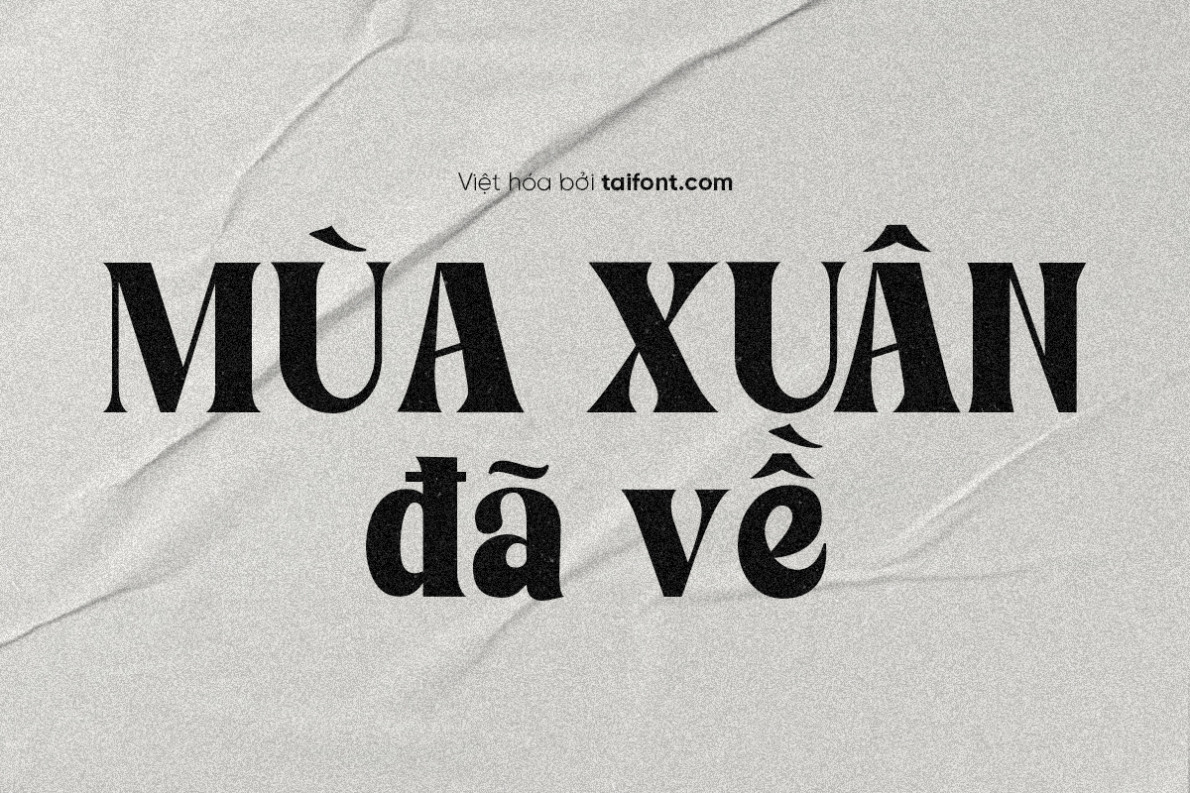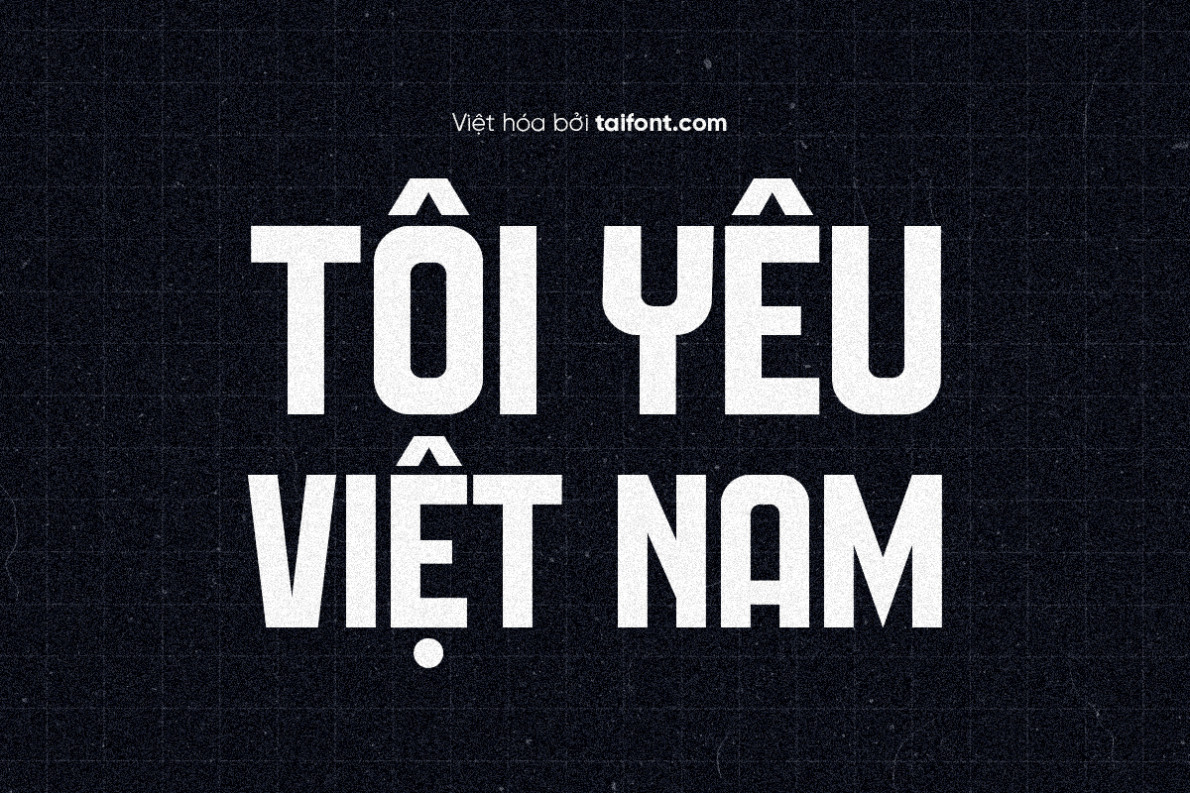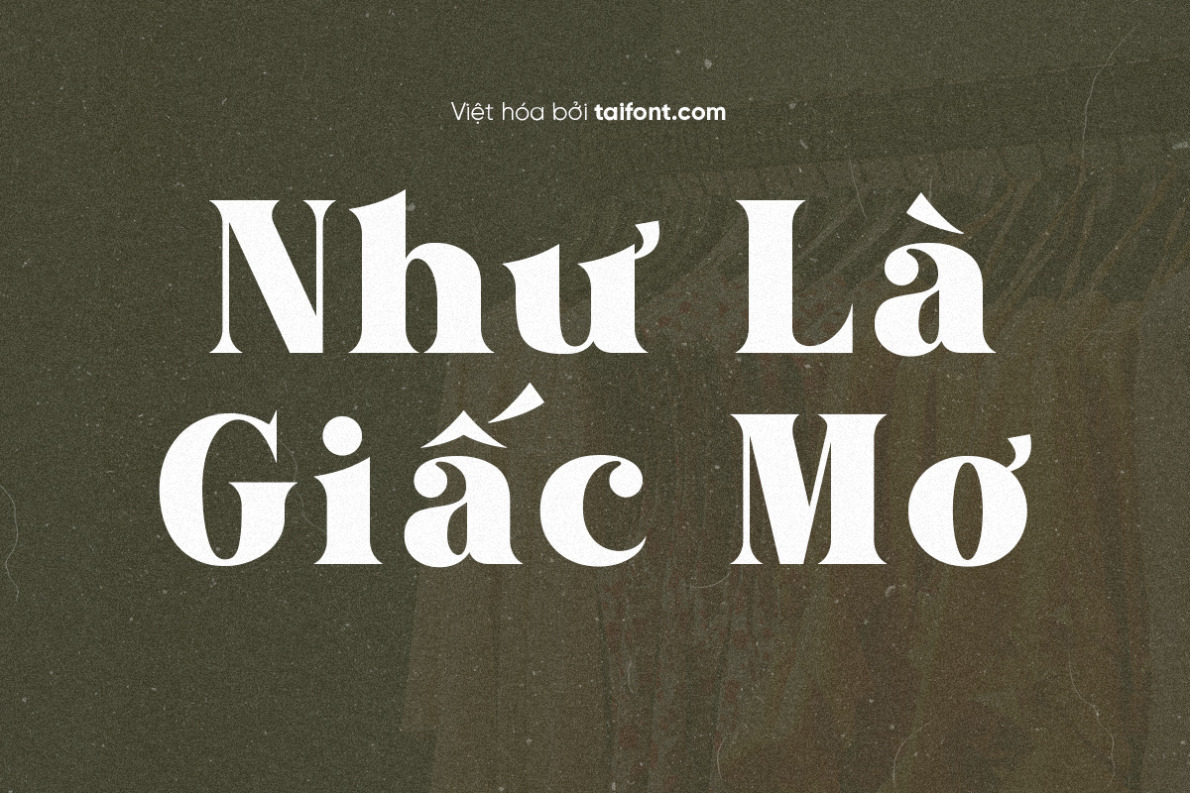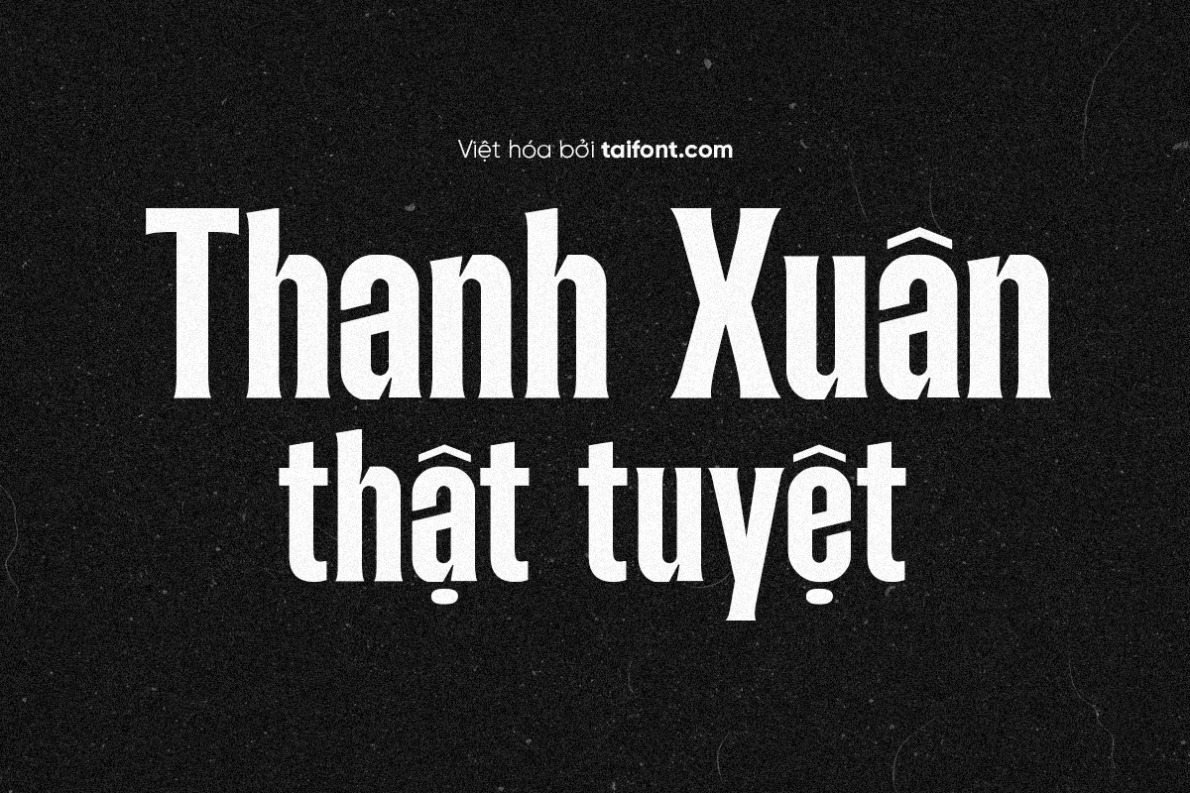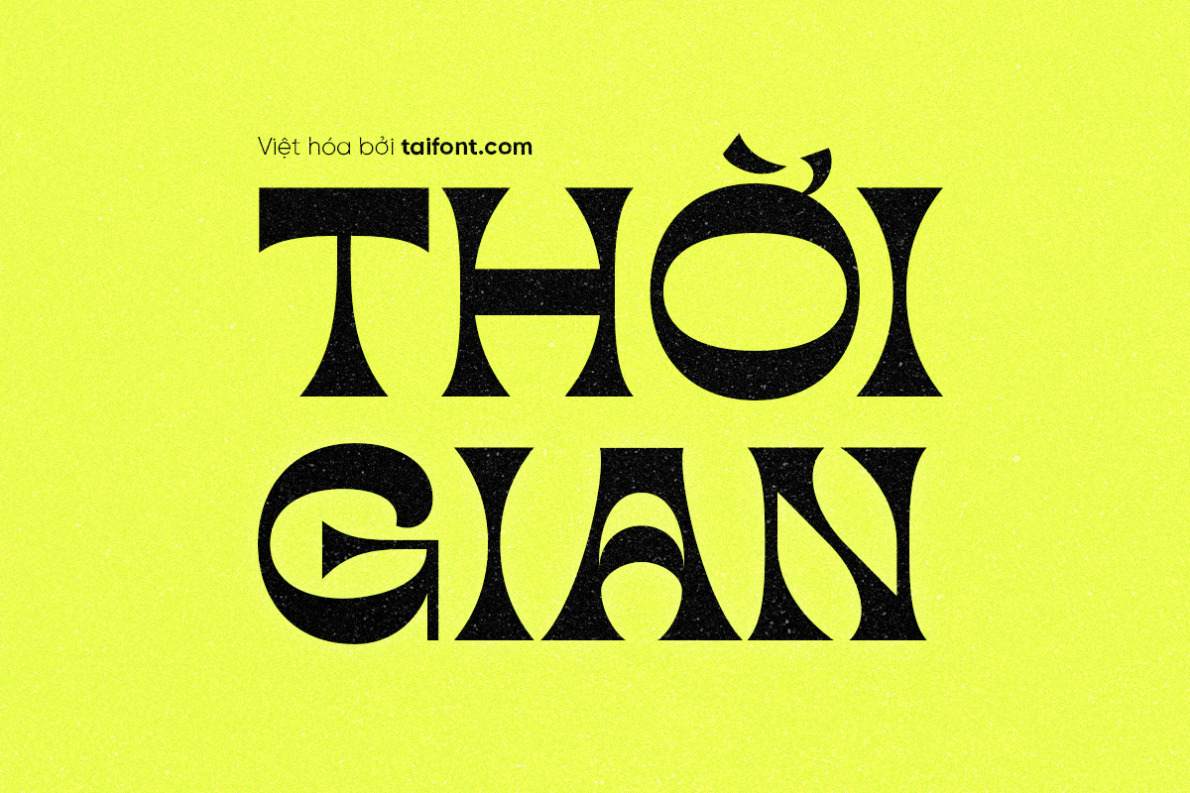
Tổng hợp 5 font Việt hóa tiêu đề đẹp
Tổng hợp 5 font Việt hóa tiêu đề đẹp, sử dụng cho tiêu đề thiết kế, soạn thảo slide powerpoint
Top 1: Font Việt hóa TF Morans | Link tải
Font Việt hóa TF Morans là một phông chữ serif thanh lịch hiện đại được tạo ra bởi alit design với các chữ ghép và chữ thay thế thời trang, mang lại sự linh hoạt tối đa trong thiết kế.
Cho dù bạn đang hướng đến vẻ ngoài hiện đại bóng bẩy hay cảm giác lấy cảm hứng từ phong cách cổ điển
Top 2: Font Việt hóa TF TAN – KINDRED | Link tải
Font Việt hóa TF TAN – KINDRED là một phông chữ hiển thị tương phản quang học có bản chất tinh nghịch và vui nhộn
Top 3: Font Việt hóa TF Rogbold | Link tải
Font Việt hóa TF Rogbold là một font Việt hóa có nét đậm, đường nét thiết kế tinh tế.
Font phù hợp với các thiết kế tiêu đề nổi bật, gây chú ý.
Top 4: Font Việt hóa TF Avone Series | Link tải
Font Việt hóa TF Avone Series có nét đậm, là font có chân hiện đại và thanh lịch.
Font phù hợp với các thiết kế sử dụng tiêu đề rõ ràng, dễ dàng nhìn thấy và gây ấn tượng tốt.
Top 5: Font Việt hóa TF Kemone | Link tải
Font Việt hóa TF Kemone là font chữ không chân mạnh mẽ, nét font dày dặn được thiết kế cực kỳ chỉnh chu. Font phù hợp với các dạng tiêu đề thể hiện rõ ràng nội dung cần hiển thị.